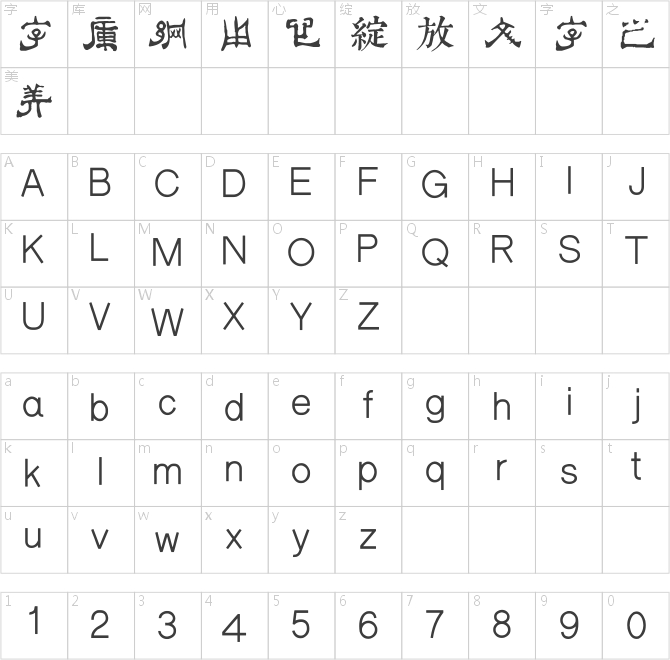
邯鄲傅山隸書千字文
邯鄲傅山隸書千字文字體下載邯鄲(清)傅山隸書千字文
傅山(1607.8.11 [1-2]  -1684.8.2)明清之際道家思想家、書法家、醫學家。初名鼎臣,字青竹,改字青主,又有濁翁、觀化等別名,漢族,山西太原人。傅山自稱為老莊之徒,他自己也在很多場合與作品中反復強調、自陳:“老夫學老莊者也”、“我本徒蒙莊”、“吾師莊先生”、“吾漆園家學”。 自覺繼承道家學派的思想文化。他對老莊的“道法自然”、“無為而治”、“泰初有無”、“隱而不隱”等命題,都作了認真的研究與闡發,對道家傳統思想作了發展  ,常以老莊之徒自居。 傅山于學無所不通,經史之外,兼通先秦諸子,又長于書畫醫學。北京大學教授、引碑入草開創者的李志敏評價:“傅山的草書圈眼多,繁而不亂,于郁勃渾脫之中,又有逸巖之態”。 著有《霜紅龕集》等。一些武俠小說里,傅山被描寫為武俠高手。他是著名的道家學者,哲學、醫學、內丹、儒學、佛學、詩歌、書法、繪畫、金石、武術、考據等無所不通。他被認為是明末清初保持民族氣節的典范人物。傅青主與顧炎武、黃宗羲、王夫之、李颙、顏元一起被梁啟超稱為“清初六大師”。著有《傅青主女科》《傅青主男科》等傳世之作,在當時有“醫圣”之名。《清史稿》卷五百一有傳。
邯鄲傅山隸書千字文字體邯鄲(清)傅山隸書千字文字庫是一款讓人賞心悅目、百看不厭的中文字體,適合各類廣告和產品包裝設計應用,字體大小6.45MB,格式為ttf字體,上傳用戶是邯鄲字庫,作者/版權方為韓紹杰